¡Hola de nuevo! En nuestro anterior artículo Consejos lettering para principiantes con rotulador de pincel ya vimos algunas consideraciones a tener en cuenta antes de empezar a dibujar lettering partiendo de la base de una caligrafía hecha con rotulador de punta de pincel o con un pincel, en donde los trazos finos hacia arriba y los trazos gruesos hacia abajo son la base. Allí os dimos consejos sobre qué papel y rotulador elegir, sobre la idea de parar entre trazos, ir lento y escoger bien el tamaño del trazo dependiendo del tamaño del pincel. Hoy os vamos a proponer un ejercicio de lettering para principiantes con los trazos básicos que tenéis que practicar antes de escribir las letras del alfabeto. Antes de nada, os queremos indicar que hemos utilizado el cuaderno Rhodia Dotpad y un rotulador Koi de Sakura color Cerulean Blue.
Trazos diagonales y rectos
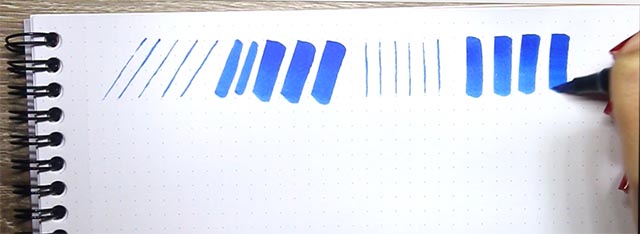
Tenéis que empezar haciendo trazos finos hacia arriba y trazos gruesos hacia abajo en diagonal y en vertical, tal y como vemos en esta parte del ejercicio. Os servirá para hacer letras como la «b», la «d», la «h», la «l», la «p», la «t» y otras letras, dependiendo del alfabeto que elijáis.
Trazos en forma de U
Este otro trazo en forma de «U» es muy práctico, evidentemente, para escribir la letra «u», pero también para escribir la letra «v», la «w» y la «y», entre otras.
Trazos en forma de U invertida
El siguiente trazo es el que tiene forma de puente o de U invertida, como prefiráis. Es muy útil para escribir bien luego las letras «n», «m», la «h», la «i», la «p» y la «z», aunque siempre depende de la forma que le deis a cada letra.
Trazos en forma de bucle ascendente y descendente
Los bucles no son fáciles de hacer, pero son muy necesarios de practicar. Os aconsejamos hacer bucles ascendentes y bucles descendentes juntos o separados, como prefiráis. Los bucles ascendentes sirven como base para las letras «b», «d», «h», «k», «l», entre otras. En cuanto a los bucles descendentes, son la previa para escribir la «f», la «j», la «q», la «y», la «z» y otras letras.
Trazos ovalados
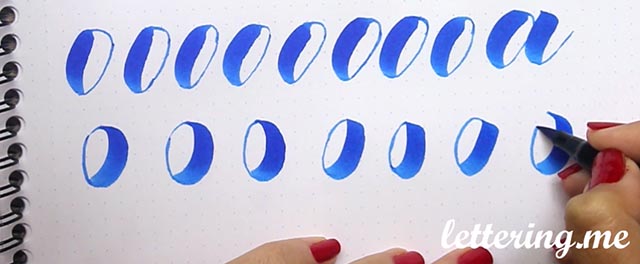
Controlar los trazos ovalados hacia un lado y hacia el otro no es nada fácil, lleva mucha práctica, así que empezad cuanto antes a escribirlos. No os volváis locos si no quedan perfectos, no pasa nada. Estos trazos sirven para escribir las letras «a», «o», «c», «d», «e», «q» y alguna otra letra más.
Vídeo con los trazos básicos paso a paso
Como siempre, esperamos que estos consejos lettering para principiantes y para escribir los trazos básicos con rotuladores de punta de pincel donde se combinan trazos finos y trazos gruesos os haya sido de ayuda. Os queremos recordar que para que os salgan bien necesitáis mucha paciencia y muchísima práctica, así que no desesperéis porque os acabarán saliendo. ¡Nos leemos pronto!